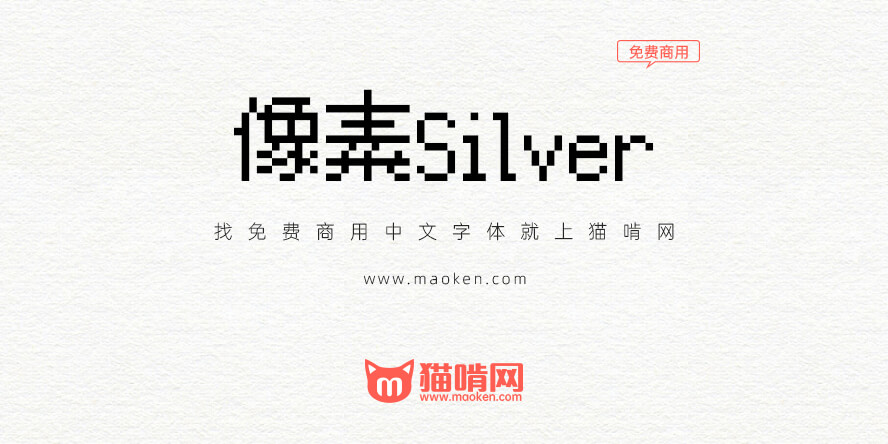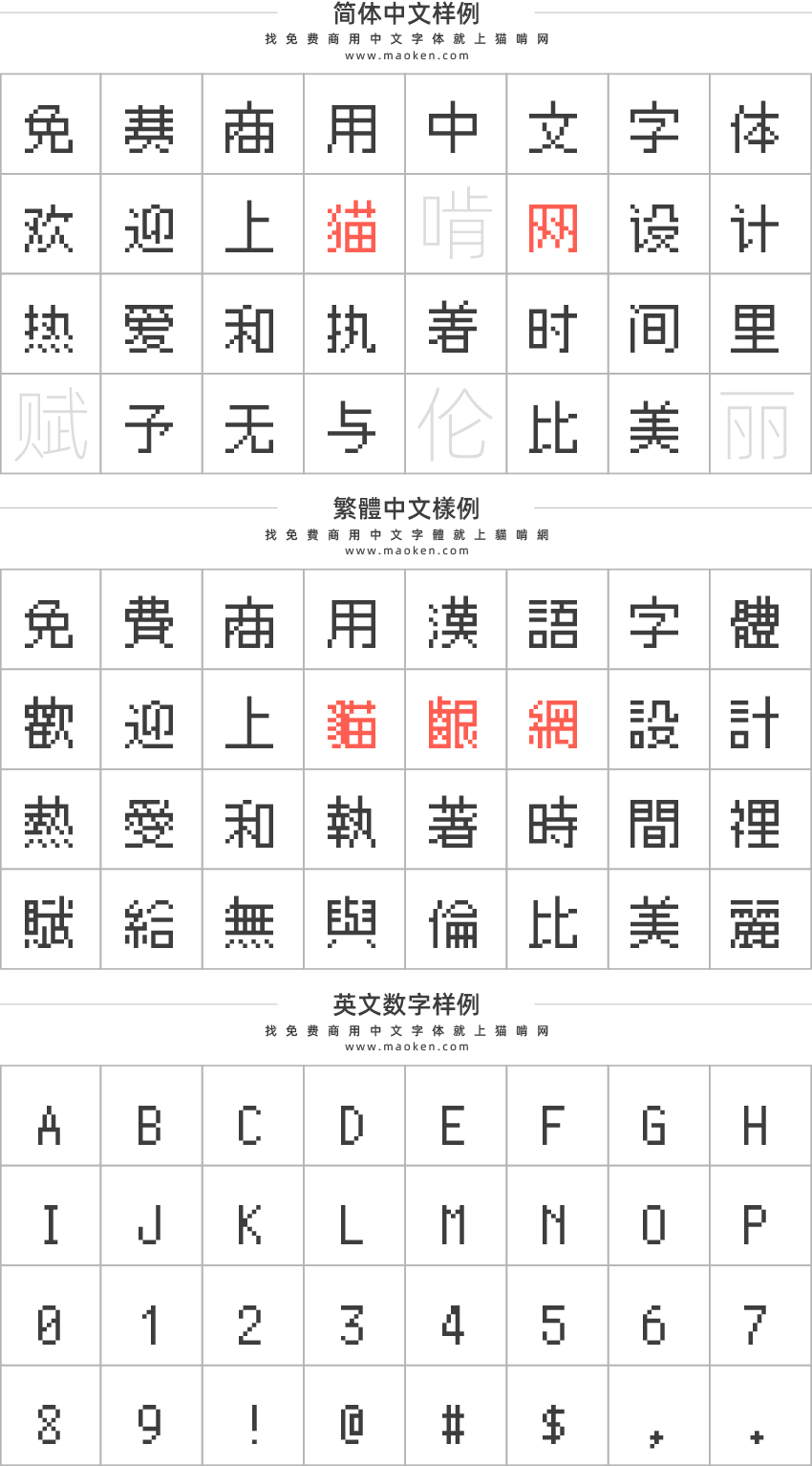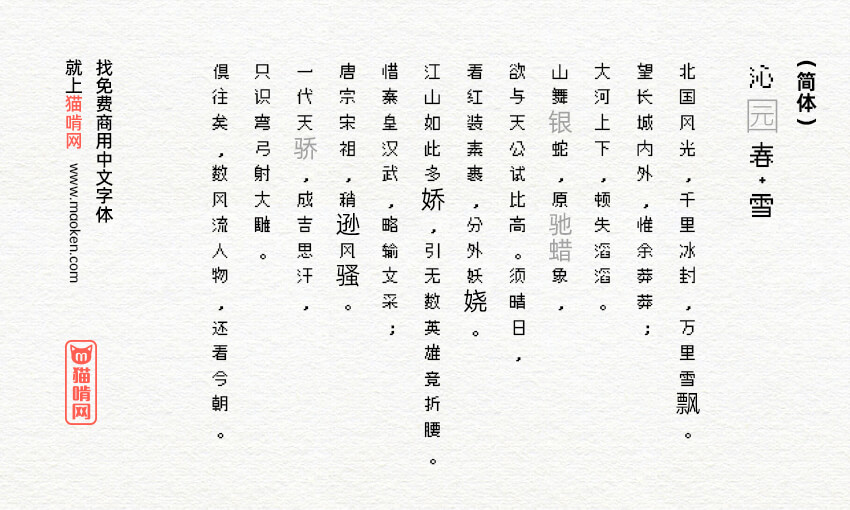
| 字体作者:Poppy Works x Wolfgang Wozniak (外国) | 字体字重:1个 |
感谢您对Silver的关注,Silver是游戏和游戏爱好者的多语言首选像素字体。它内置了符合TRC和Lotcheck标准的游戏手柄按钮,同时还提供了完整的键盘和鼠标提示!您再也不需要把图像加在文本字段上了!
这是一个正在进行的项目,将会持续更新新的Unicode字符。我们的目标是成为像素游戏和应用程序的实际字体。当您在最终项目中使用Silver时,可以考虑给我们捐款。
现在有哪些字体使用了Silver?
- 「Gunbrella」
- 「Slave Zero X」
- 「SIGNALIS」
- 「Infernax」
- 「Crypt of the NecroDancer」
- 「What Lies in the Multiverse」
- 「Final Fantasy Pixel Remasters (mod)」
- 「World of Horror」
- 「Blazing Beaks」
- 「Super Skull Smash GO! 2 Turbo」
- 「Bones ‘n’ Bullets」
- 「Halloween Forever」
- 「Garden for Gato」
- 「Melon Journey: Bittersweet Memories」
- 「Jack Move」
- 「ComPressure」
- 「Exquisite Ghorpse Story」
支持哪些语言和字形?
作者: Poppy Works, Wolfgang Wozniak
主要贡献者: Itou Hiro (PixelMPlus), leedheo (DOSGothic), ぶち
自带手柄图标这点太方便了,不用再单独画图。
最新cjk update 13发布于2023.9.30,距今243天【感觉可以更新一波了,应该在网友提需求下补了挺多简体了
很好看的字体!!!